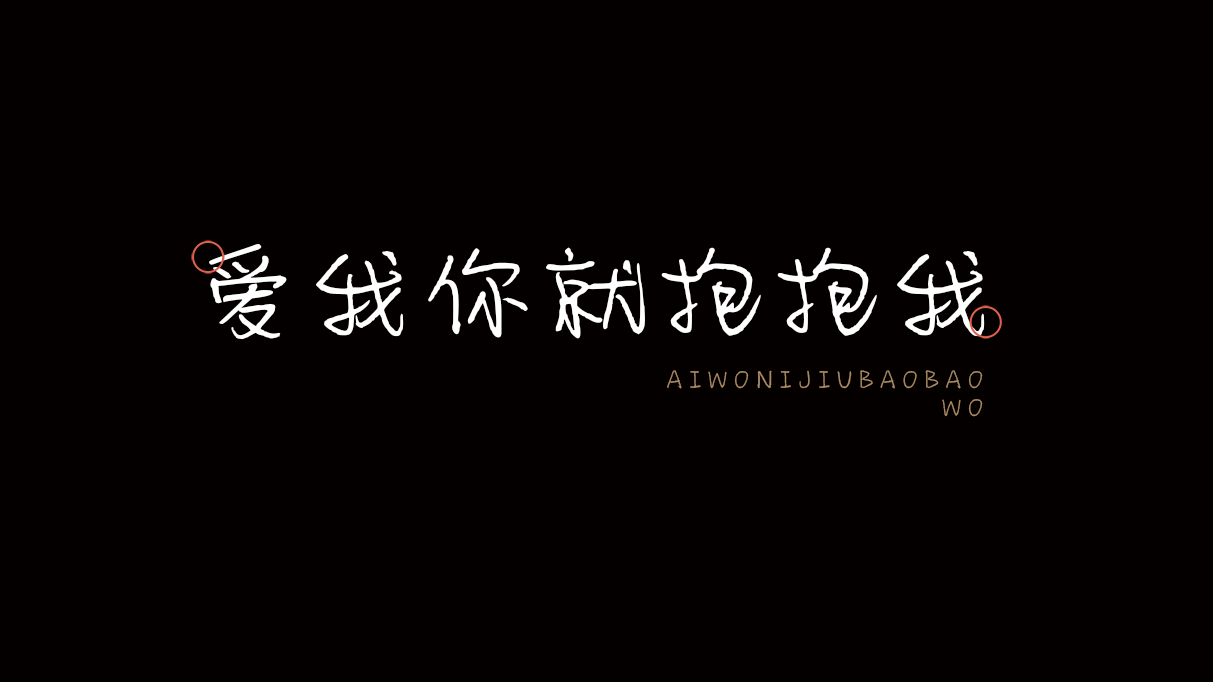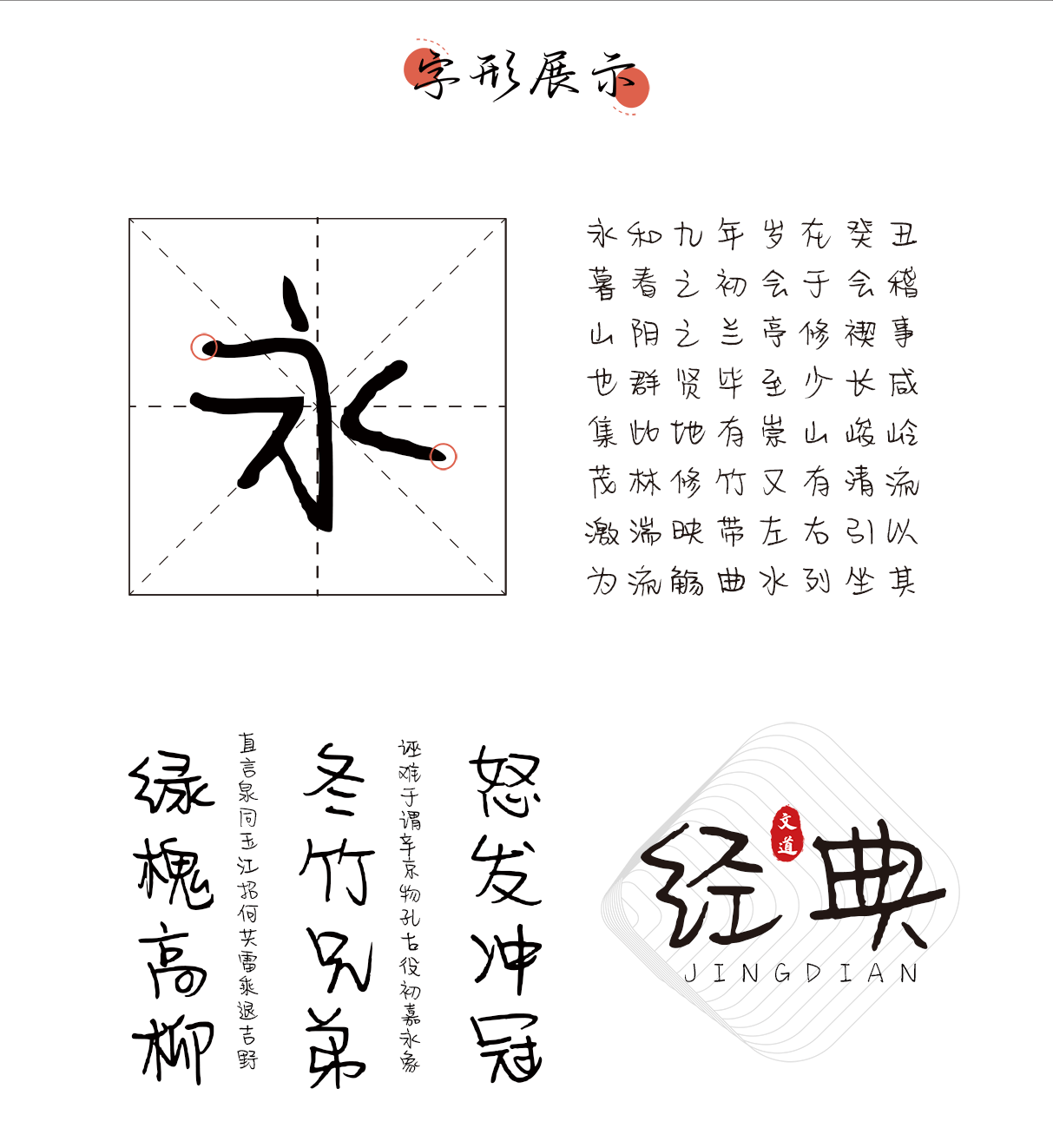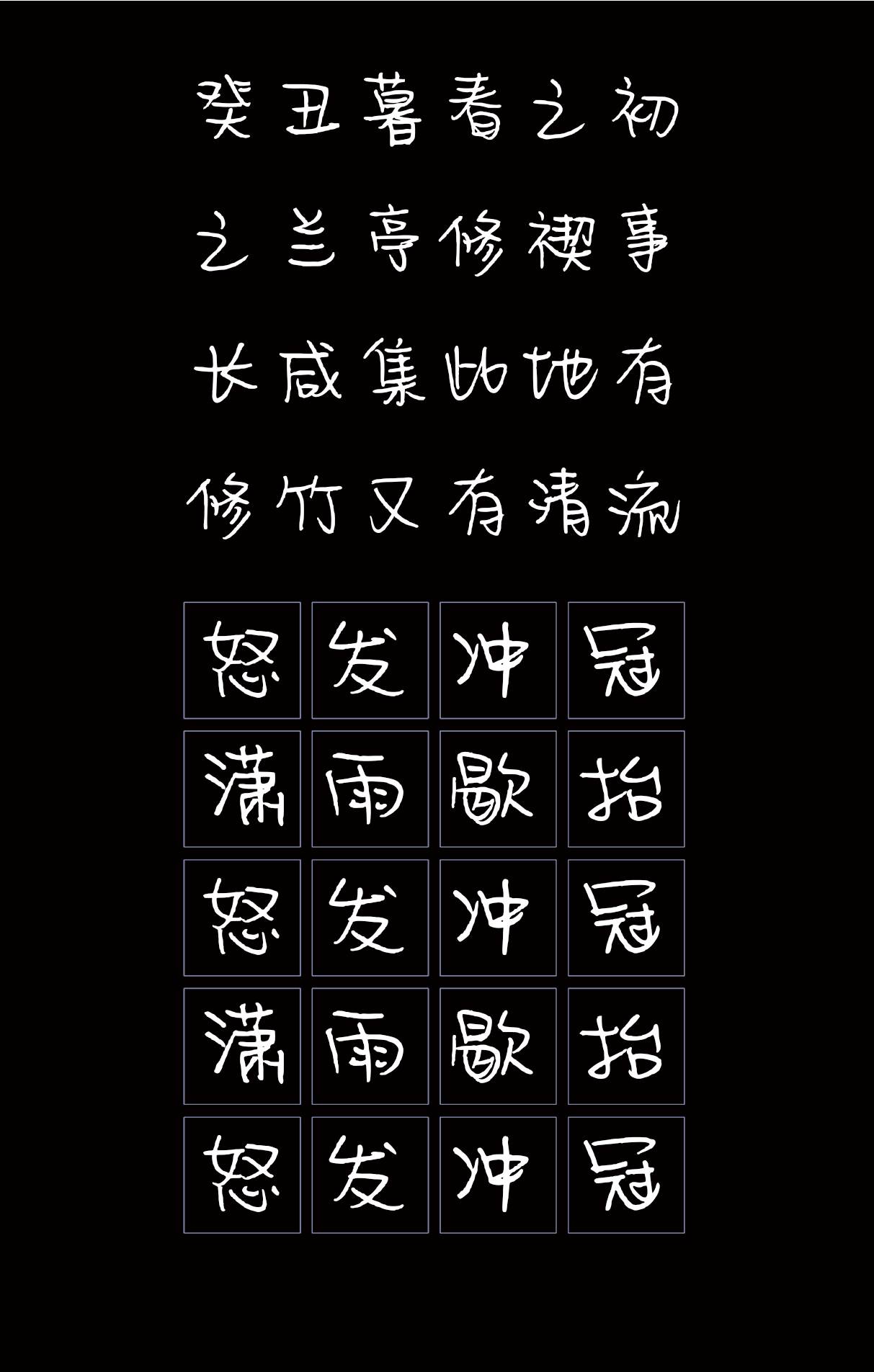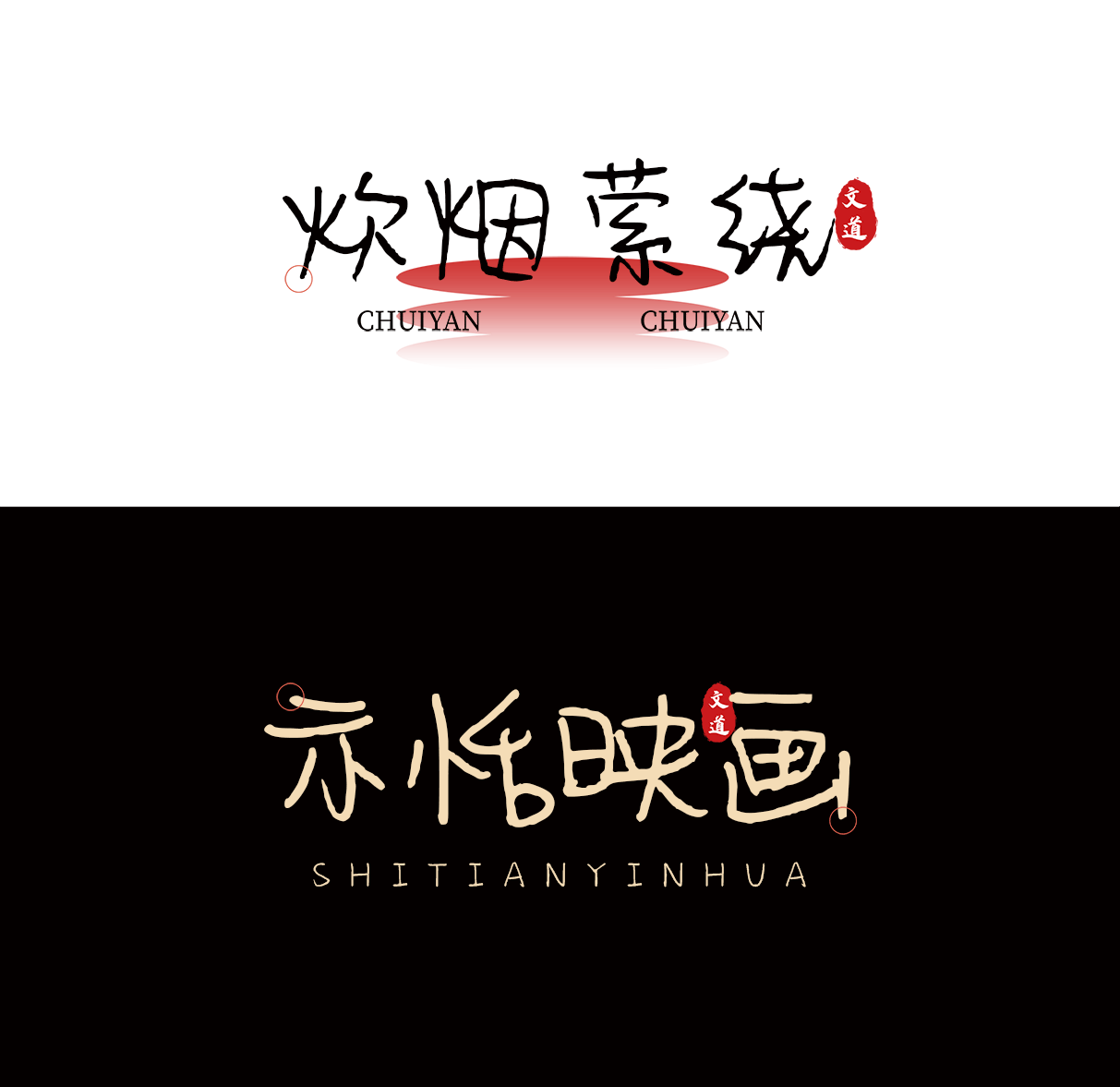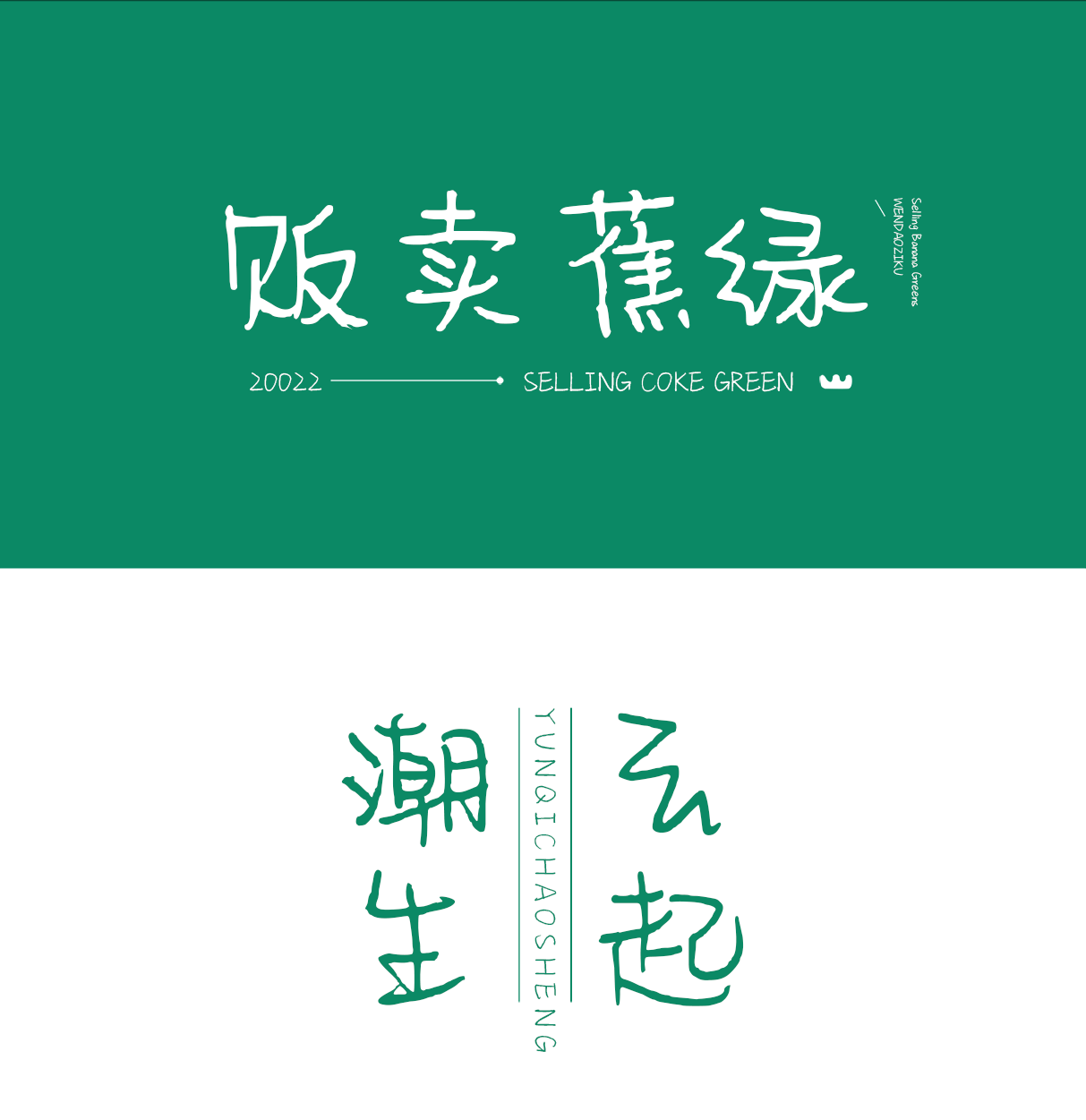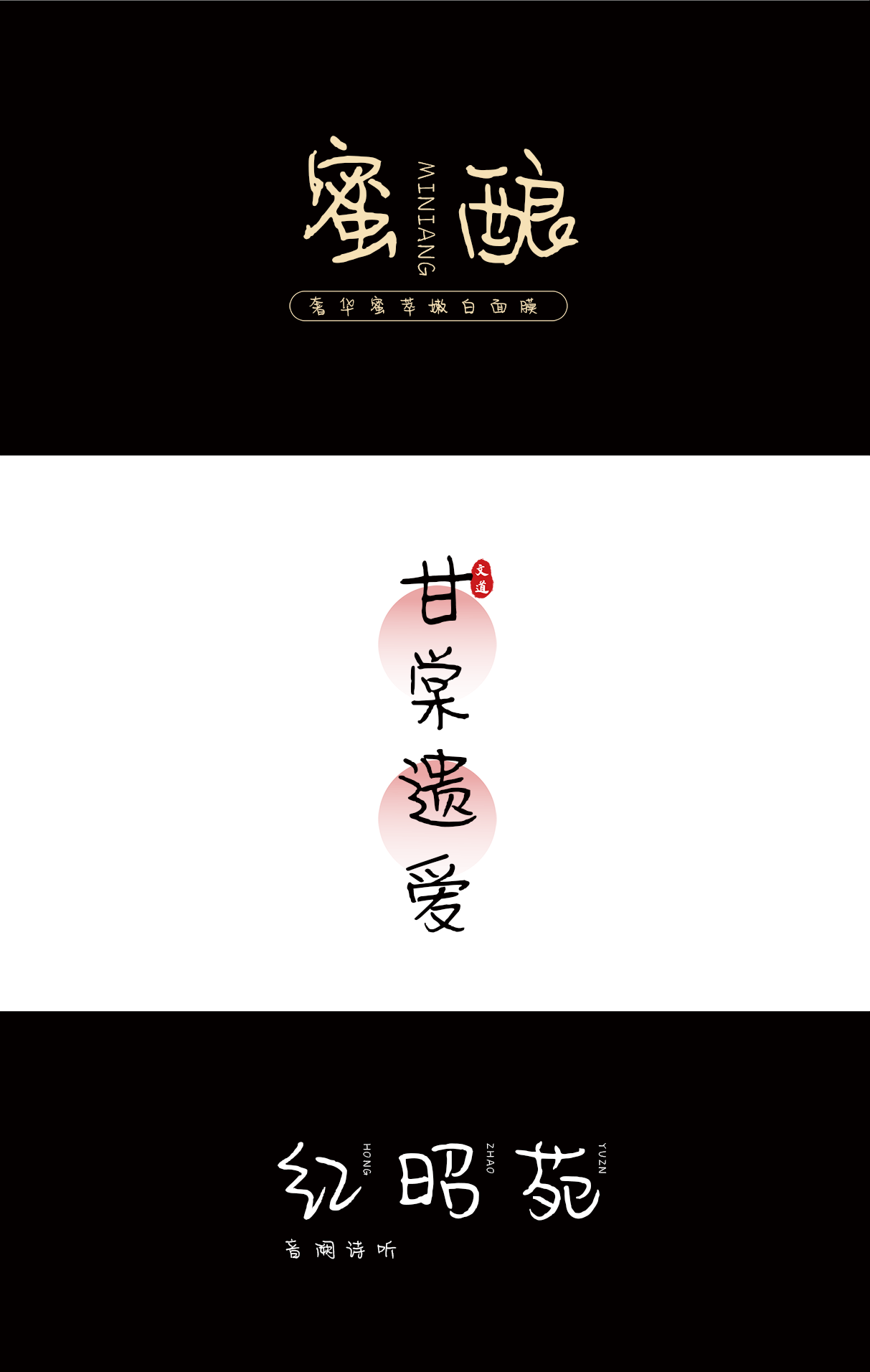
| 字体名称: | 爱我你就抱抱我 |
| 所属分类: | 创意体 可爱 |
| 简介: | 【爱我你就抱抱我】是一款可商用创字体,其字形也是偏圆润型,给人的感觉是非常的亲和又舒适,该字包含6763个中文、字母、符号和数字,具有非常好的视觉感受,适合于新媒体、电商、海报的标题和logo除了满足传统印刷媒介的标题,还适用于屏幕显示、短视频字幕、综艺节目字幕和产品包装设计。 |